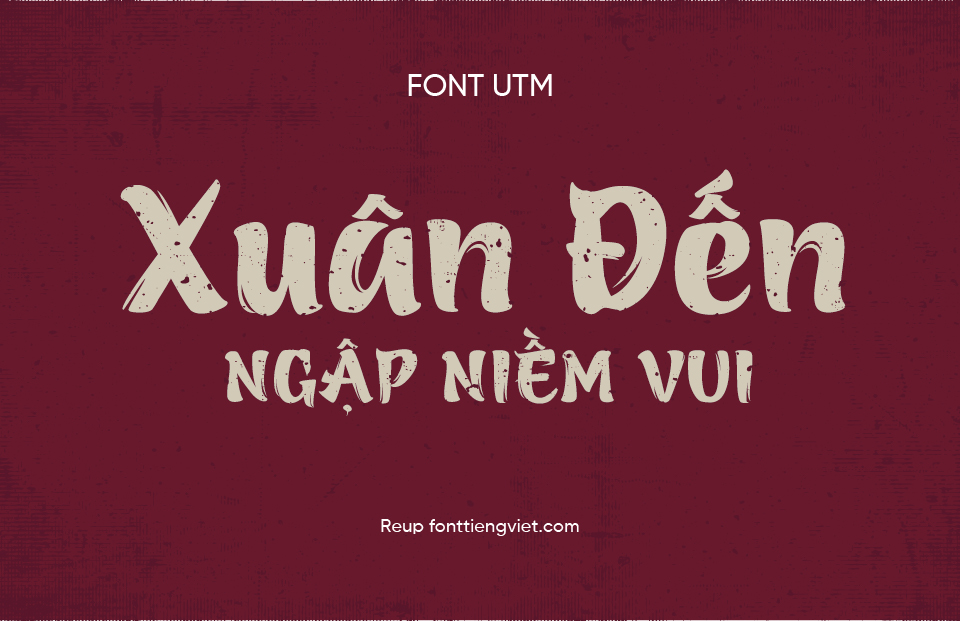
Font việt hóa UTM Azuki – Tết – Nét chữ ấn tượng cho thiết kế ngày xuân
Giới thiệu về Font việt hóa UTM Azuki – Tết
Trong thế giới đồ họa hiện đại, việc lựa chọn một Font Chữ phù hợp đóng vai trò then chốt để truyền tải cảm xúc của tác phẩm. Đặc biệt, khi không khí mùa xuân đang cận kề, Font việt hóa UTM Azuki – Tết trở thành cái tên được tìm kiếm nhiều nhất bởi cộng đồng thiết kế Việt Nam. Đây là một bộ phông chữ mang phong cách viết tay mềm mại, tự nhiên nhưng không kém phần vui tươi, cực kỳ thích hợp cho các chủ đề lễ hội. Với sự hỗ trợ đầy đủ bảng mã tiếng Việt, người dùng có thể dễ dàng tạo ra những câu chúc ý nghĩa mà không lo bị lỗi hiển thị.
Ưu điểm nổi bật của bộ font UTM Azuki
Ưu điểm lớn nhất của Font việt hóa UTM Azuki – Tết chính là sự linh hoạt và tính ứng dụng cao. Font chữ này mô phỏng nét bút lông sắc sảo, gợi nhớ đến những bức thư pháp truyền thống nhưng lại có nét thanh thoát của phong cách Nhật Bản hiện đại. Các bạn học sinh và giáo viên có thể sử dụng font này để thiết kế thiệp chúc mừng, làm bảng tin lớp học hoặc trang trí các tệp thuyết trình về chủ đề Tết Nguyên Đán. Sự cân bằng giữa tính thẩm mỹ và độ đọc hiểu rõ ràng giúp Azuki ghi điểm tuyệt đối trong mắt người dùng.
Cách ứng dụng Font việt hóa UTM Azuki – Tết trong thiết kế
Để tối ưu hóa vẻ đẹp của Font việt hóa UTM Azuki – Tết, bạn nên kết hợp với những gam màu nóng như đỏ, vàng hoặc cam. Những màu sắc này không chỉ tượng trưng cho may mắn mà còn làm nổi bật các đường cong uốn lượn của phông chữ. Ngoài việc dùng cho tiêu đề, bạn cũng có thể áp dụng cho các đoạn văn ngắn hoặc trích dẫn để tạo điểm nhấn nghệ thuật. Việc cài đặt font vô cùng đơn giản, giúp bất kỳ ai cũng có thể tiếp cận và sáng tạo những sản phẩm mang đậm bản sắc cá nhân.
Kết luận và trải nghiệm người dùng